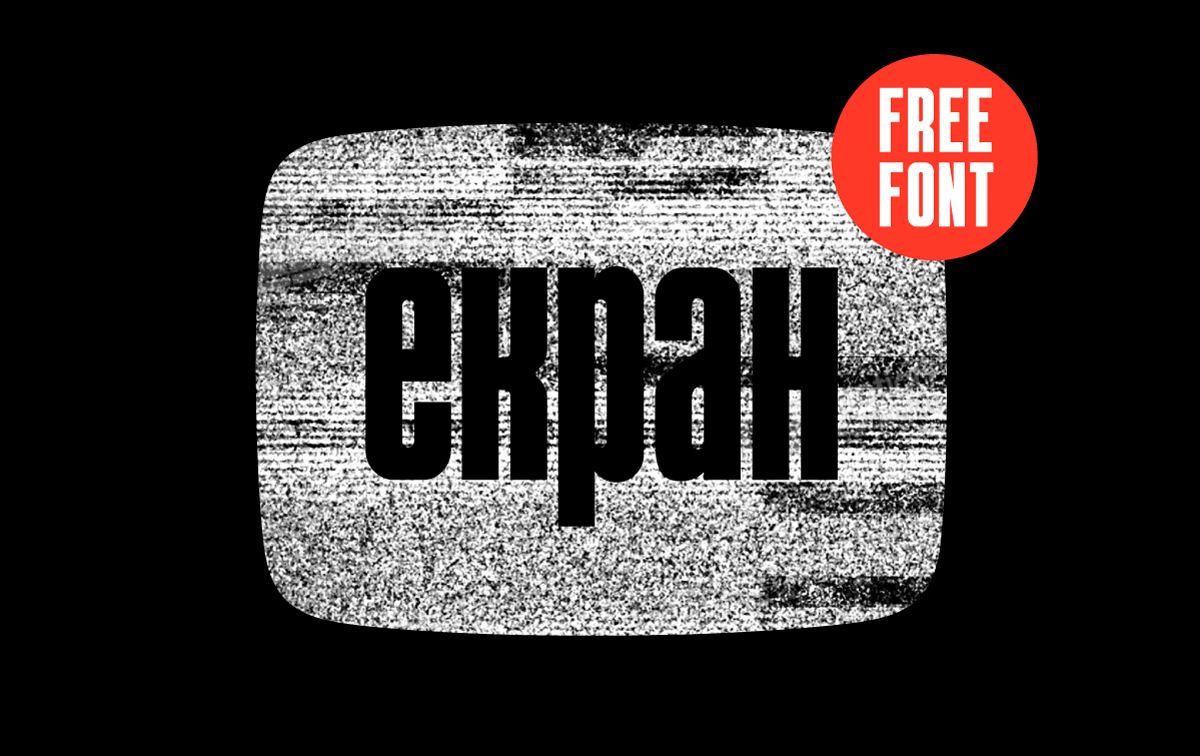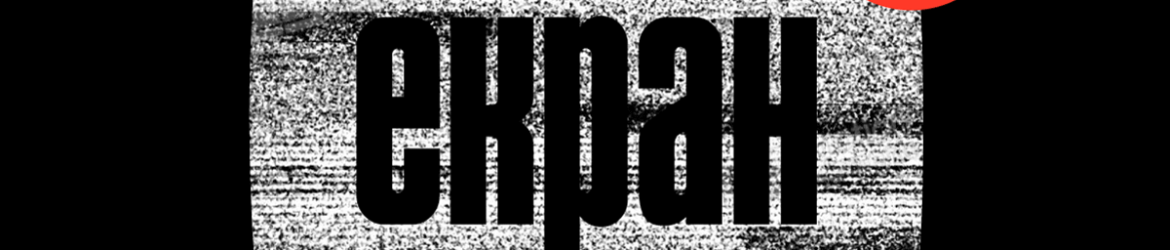
A fonte Ekran Typeface é uma opção incrível para designers que buscam um estilo moderno e minimalista no design visual. Ela foi criada por Nebojsa Gelevski – Bane, inspirada pelos headlines do periódico semanal Macedônio Ekran de 1970s. A fonte é uma elegante tipografia sans-serif em caixa alta, com um formato ideal para criar logos e títulos memoráveis. Seu nome em português significa “Pantura”, o que fazê-lo perfeito para projetos visuais desejando algo moderno e sofisticado. Ekran oferece uma aparência minimalista e minimalista, mas não é fraca; sua estrutura firme e alegre garante um equilíbrio entre simplicidade e elegância que pode transformar qualquer design em um verdadeiro destaque. Esta fonte vem em uma categoria de tipografia display, o que significa que ela foi projetada para ser visualmente chamativa e impactante. Ideal para criar visuais atraentes e memoráveis, Ekran é perfeita para trabalhos de identidade visual, logos profissionais e design gráfico.